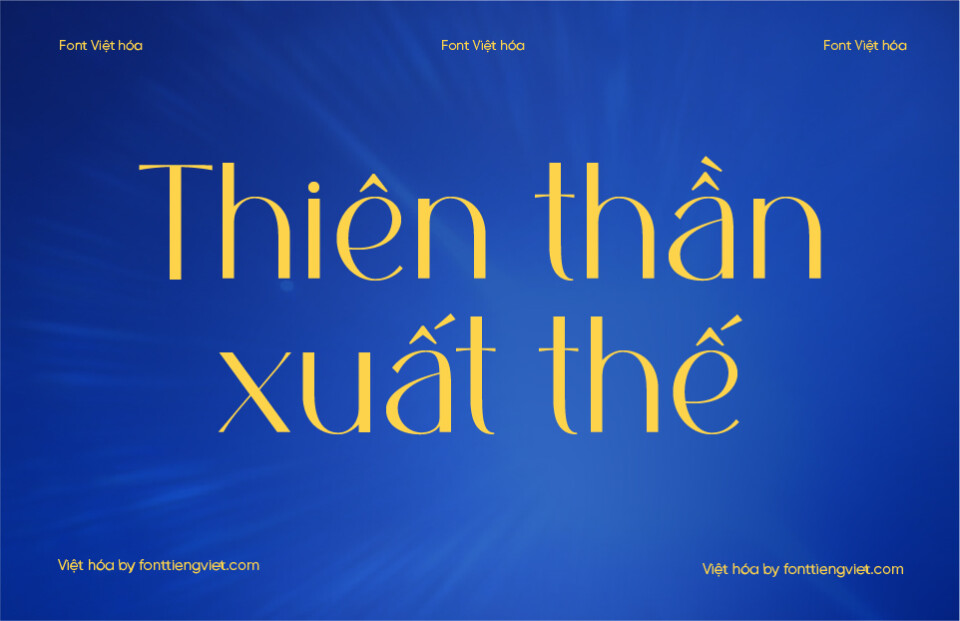
Font Việt hóa 1FTV VIP Romeda
Giới thiệu về Font Việt hóa 1FTV VIP Romeda
Trong thế giới đồ họa hiện đại, việc tìm kiếm một bộ Font Miễn Phí chất lượng và hỗ trợ tiếng Việt đầy đủ là ưu tiên hàng đầu của các nhà thiết kế. Font Việt hóa 1FTV VIP Romeda nổi lên như một giải pháp hoàn hảo, kết hợp giữa nét cổ điển sang trọng và sự tinh tế của phong cách Serif hiện đại. Đây là bộ phông chữ được tinh chỉnh kỹ lưỡng, đảm bảo các dấu câu tiếng Việt không bị lỗi chân chữ hay dính chữ, giúp văn bản trở nên chuyên nghiệp hơn bao giờ hết. Với những đường nét thanh mảnh nhưng chắc chắn, bộ font này mang lại cảm giác tin cậy và thẩm mỹ cao cho người xem ngay từ cái nhìn đầu tiên.
Đặc điểm nổi bật của Font Việt hóa 1FTV VIP Romeda
Phong cách thiết kế Serif độc đáo
Font Việt hóa 1FTV VIP Romeda sở hữu các đường nét uốn lượn tinh xảo ở phần chân chữ, tạo nên một cấu trúc cân đối và hài hòa. Điều này giúp bộ font cực kỳ phù hợp cho các tiêu đề sách, bìa tạp chí hoặc các ấn phẩm truyền thông đòi hỏi sự trang trọng. Khả năng hiển thị sắc nét trên cả màn hình kỹ thuật số và bản in vật lý giúp nó trở thành công cụ đắc lực cho các bạn học sinh trong việc làm báo tường hoặc trang trí tiểu luận. Sự kết hợp giữa độ tương phản cao của nét thanh và nét đậm giúp nội dung trở nên sống động, thu hút sự chú ý của độc giả một cách tự nhiên nhất mà không gây cảm giác nặng nề.
Tính ứng dụng linh hoạt trong đa dạng dự án
Không chỉ giới hạn trong các thiết kế in ấn, Font Việt hóa 1FTV VIP Romeda còn phát huy tối đa sức mạnh trong lĩnh vực xây dựng thương hiệu. Bạn có thể sử dụng bộ phông này cho thiết kế logo, bao bì sản phẩm cao cấp hoặc các thiệp mời sự kiện quan trọng. Nhờ vào bảng mã được việt hóa chuẩn chỉnh, người dùng dễ dàng gõ văn bản trên các phần mềm phổ biến như Photoshop, Illustrator hay thậm chí là Microsoft Word. Sự linh hoạt này giúp tiết kiệm thời gian chỉnh sửa thủ công, cho phép các nhà sáng tạo tập trung vào việc phát triển ý tưởng cốt lõi thay vì loay hoay khắc phục lỗi phông chữ thường gặp.
Kết luận về giá trị nghệ thuật của bộ font
Có thể khẳng định rằng, việc sở hữu bộ Font Việt hóa 1FTV VIP Romeda sẽ giúp nâng tầm mọi sản phẩm sáng tạo của bạn lên một đẳng cấp mới. Sự chỉn chu trong từng nét chữ phản ánh tâm huyết của người làm nghề và sự tôn trọng đối với ngôn ngữ Việt. Hãy nhanh tay truy cập Font Miễn Phí, Font Việt Hóa, Font Việt hóa 1FTV VIP Romeda để làm phong phú thêm kho tàng tài nguyên thiết kế của mình. Việc sử dụng đúng phông chữ không chỉ là yếu tố kỹ thuật mà còn là chìa khóa để truyền tải cảm xúc và thông điệp một cách trọn vẹn nhất đến với mọi tầng lớp người đọc trong xã hội hiện nay.